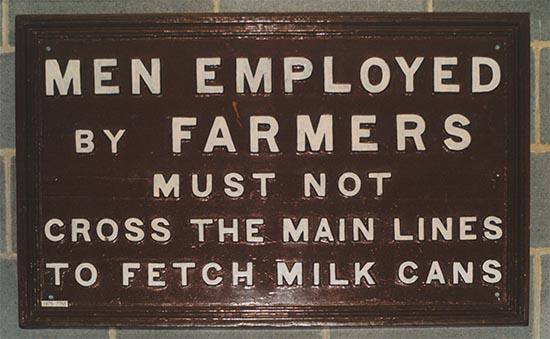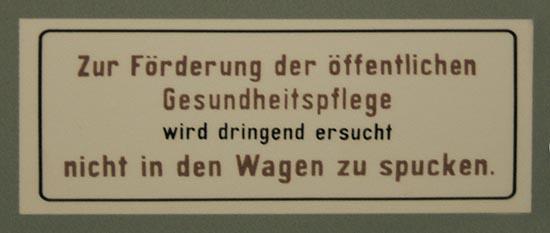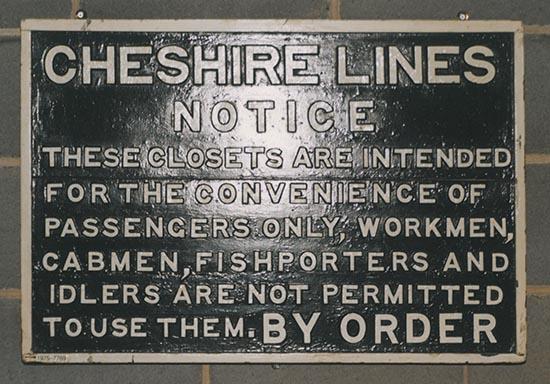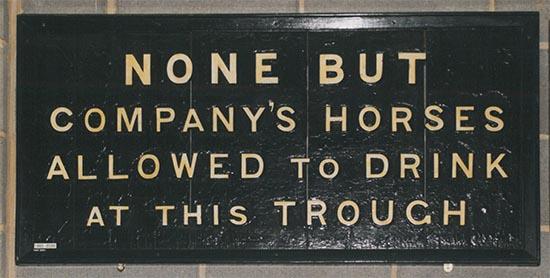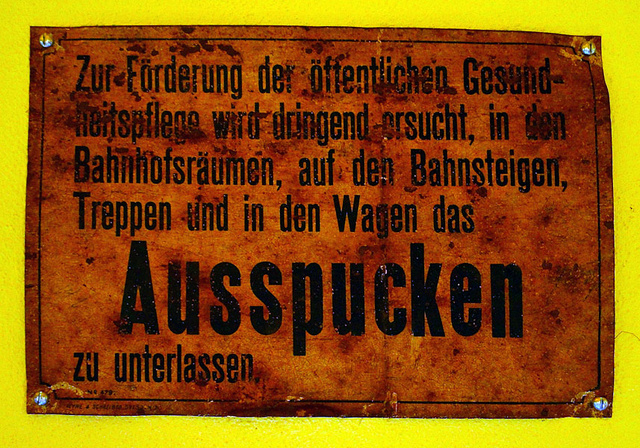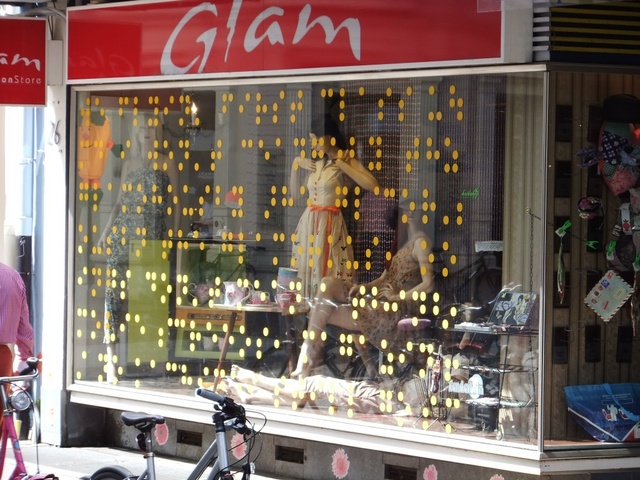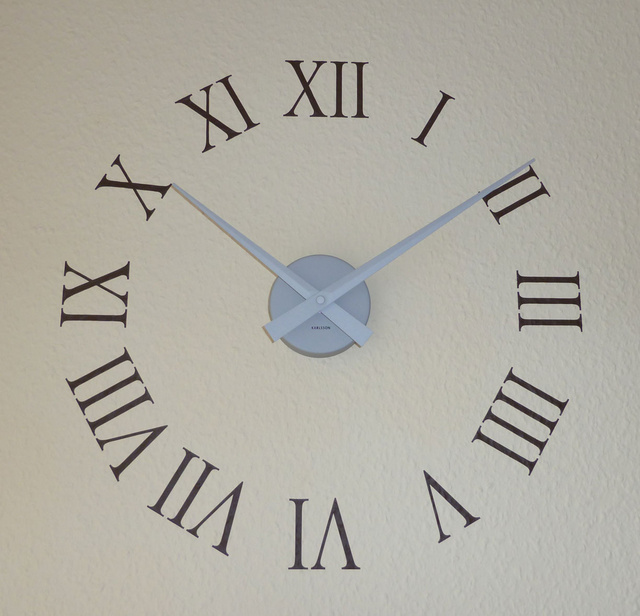
Sauber. Zu dem Friseur hätte ich auch Vertrauen.
Ich hätt’ ja eher Vertrauen, wenn’s ihm von sich aus klar ist, dass er nicht rumspucken sollte und man es ihm nicht extra verbieten müsste.
... aber ich sollte da man nichts zu sagen, da ich ja selber immer Ärger bekomme, wenn meine herunterfallenden Haare das Unfallrisiko durch Pomade verschmierten Boden erhöhen :roll:
Ich hätt’ ja eher Vertrauen, wenn’s ihm von sich aus klar ist, dass er nicht rumspucken sollte
Ich denke, das Schild richtet sich eher an die Kunden, denn der Friseur sollte es ja sowieso wissen.
§ 7 Arbeits-Ordnung
Nun, da der Meister dort die Scherenhände schwingt,
wo ja bekanntlich die Sonne aufgeht,
sind sowohl Angestellte als auch Kunden gemeint ‒
's sind doch beide Arbeiter. Klasse, nicht?!
Und um mal Arno Schmidt zu bemühen, so
sind es doch ganz eigentlich, ganz bestimmt,
wenn nicht sogar ausschließlich nur
"Erinnerungen einer Ladentürklinke"...
Ich fürchte ja fast, die Zielgruppe läuft daran blind vorbei ...
Steht da eigentlich was sinnvolles? Meine Versuche, mit Wikipedia den Anfang zu entschlüsseln, ließen nicht drauf schließen ...
Ich fürchte ja fast, die Zielgruppe läuft daran blind vorbei ...
Steht da eigentlich was sinnvolles? Meine Versuche, mit Wikipedia den Anfang zu entschlüsseln, ließen nicht drauf schließen ...
I am glam – therefore I am.
Steht da eigentlich was sinnvolles?
Wenn ich jetzt auf die Schnelle Buchstabe für Buchstabe entziffern sollte, würde
WE FLYIN' FIRST CLASS U?
MD I WON'T CEANGEBY THZ
GLAMOHOUSBY SHE GLACOR'.
OUSBN THE GLAMORKUS, OO
INGS DON'T CEAN' TB: ANB.,
MOVIE SCREEOS, MAGAZIN,
,A NOKACHICA STILL GOSM
rauskommen. Ist jetzt eher nur mittelsinnvoll ;) Allerdings sieht es so aus, als wären einige Punkte beim Aufkleben vergessen (oder von außen abgeknibbelt?) worden, denn ein paar Punkte mehr an manchen Stellen würden andere Buchstaben und damit schon sinnvollere Wörter ergeben…
Auf jeden Fall ein großartig lustiges Fundstück. Was die sich dabei wohl gedacht haben?!
Ist jetzt eher nur mittelsinnvoll ;)
Äh ...
Ja ... ;)
Allerdings sieht es so aus, als wären einige Punkte beim Aufkleben vergessen (oder von außen abgeknibbelt?) worden, denn ein paar Punkte mehr an manchen Stellen würden andere Buchstaben und damit schon sinnvollere Wörter ergeben…
Das kann sein, der Text hängt da schon ein paar Tage ...
Auf jeden Fall ein großartig lustiges Fundstück. Was die sich dabei wohl gedacht haben?!
Gute Frage ...
Aufmerksamkeit erheischen?
Die texten ihr Fenster aber öfters zu ...
Das könnte eine Serie hier werden ;-)
Vor längerer Zeit mal was in gebrochener Schrift, aber m.E.n. ohne tiefere lang-s-Regel-Kenntnisse *seufz*
WE FLYIN' FIRST CLASS U?
Ist jetzt eher nur mittelsinnvoll ;)
Also zumindest die (von mir noch mal zitierte) 1. Zeile ist perfektes Cajun English. Mit normaler Groß-/Kleinschreibung und Interpunktion hieße der Satz: »We flyin’ first class, you?« Übersetzt: »Sag mal, fliegen wir tatsächlich erste Klasse?«
Vielleicht hat der Autor ja Verbindungen nach oder eine Affinität zu Louisiana – oder hat einfach nur zu viel True Blood gesehen. Und möglicherweise sind die Punkte der unteren Zeilen einfach nur verrutscht. :-?
Hier wird noch wirklich von Hand gearbeitet … sensationell, wie ich finde.
Möge er viele Söhne zeugen, von denen wenigstens einer das Handwerk weitertreibt und möge niemand sein Auto in einen Unfall verwickeln.